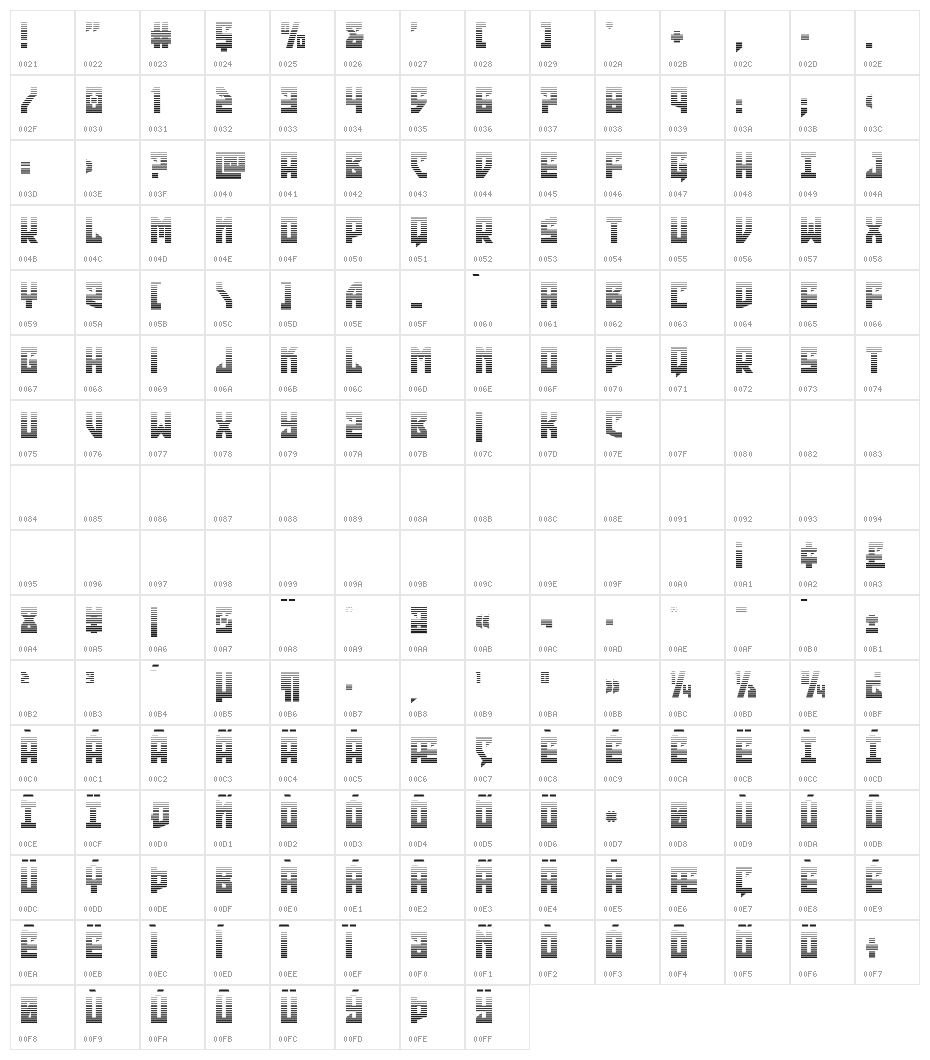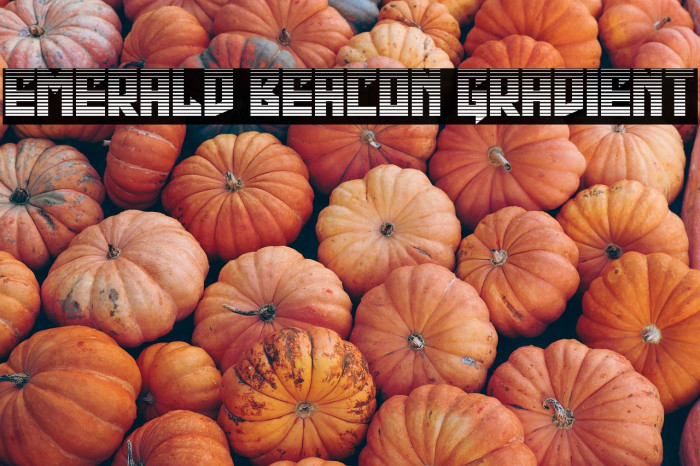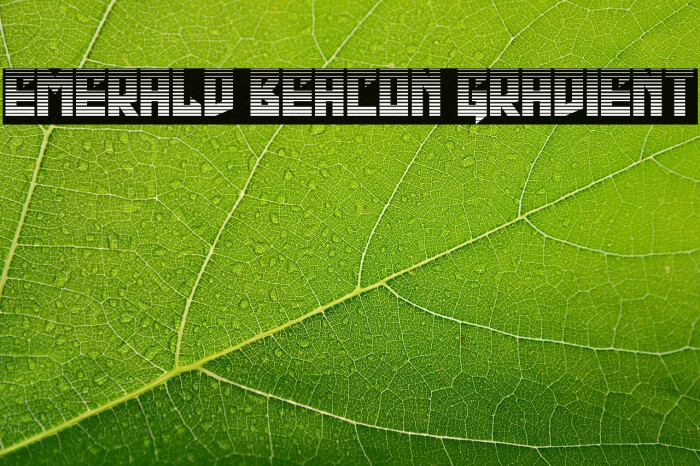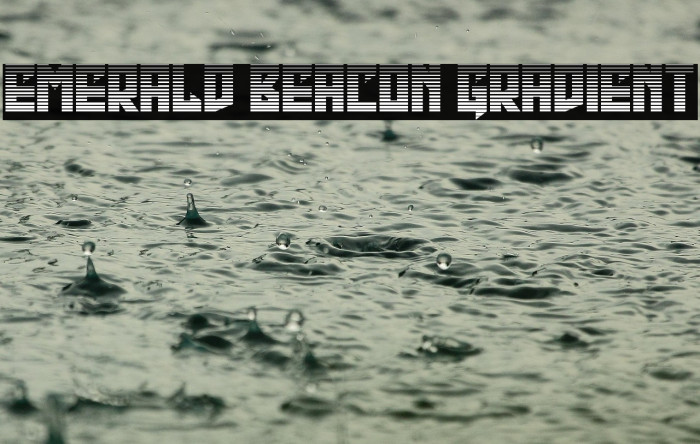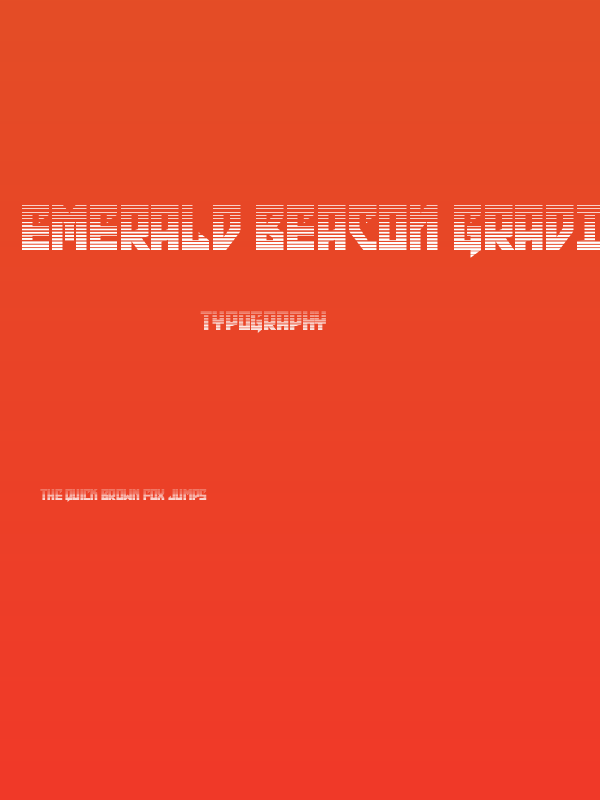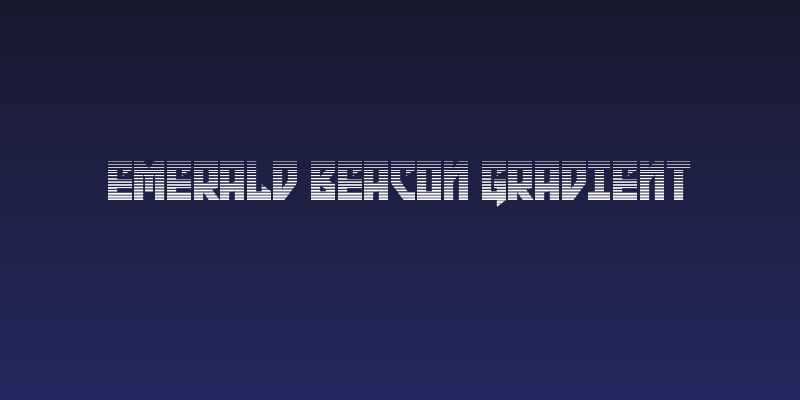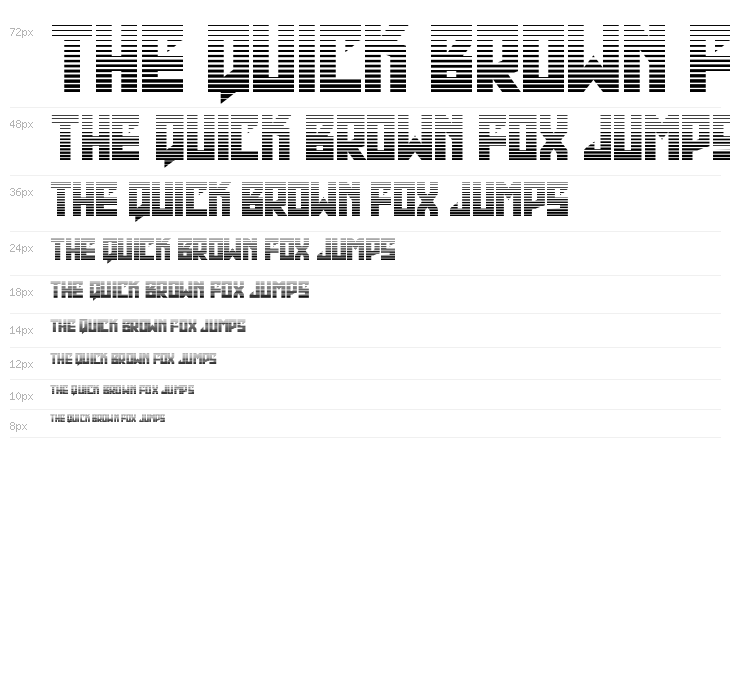
Emerald Beacon Gradient Font
| Progetti proposti | Ideal for sci-fi themed designs, modern posters, digital artwork, and branding that requires a futuristic touch. |